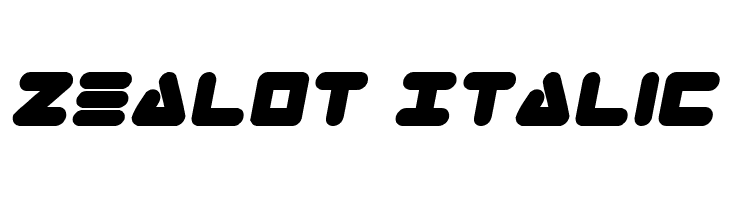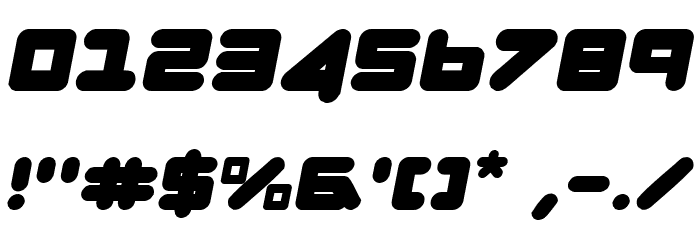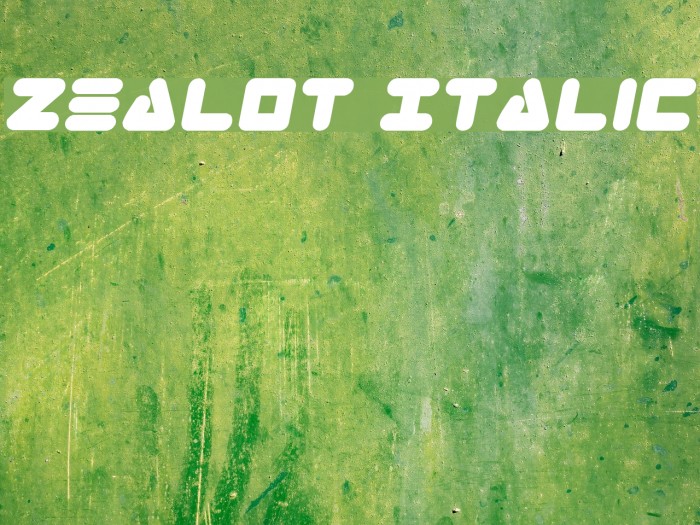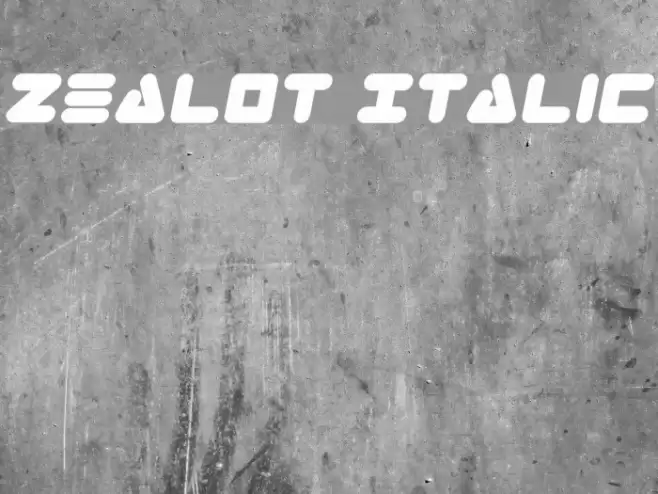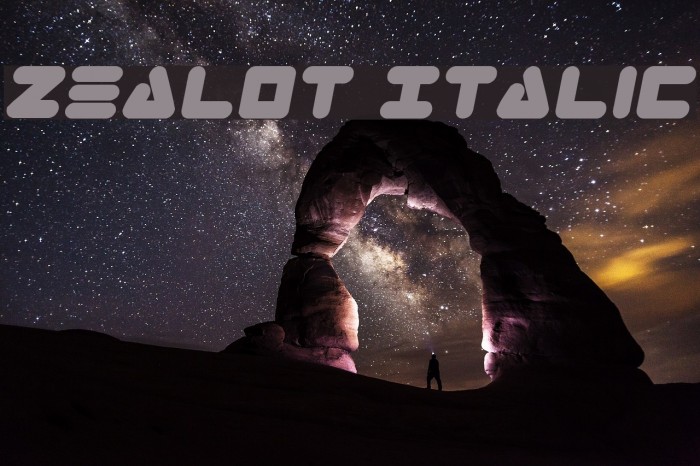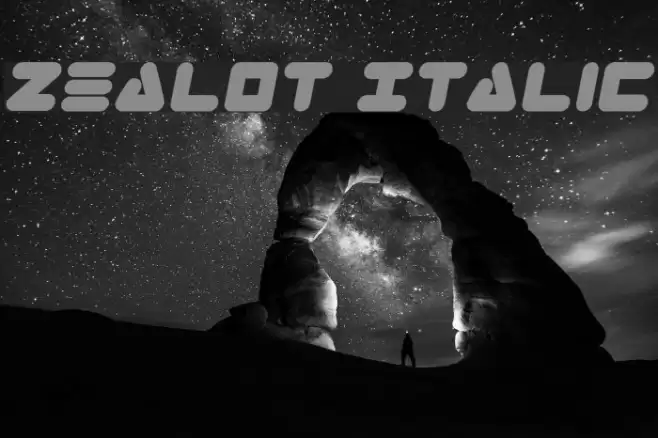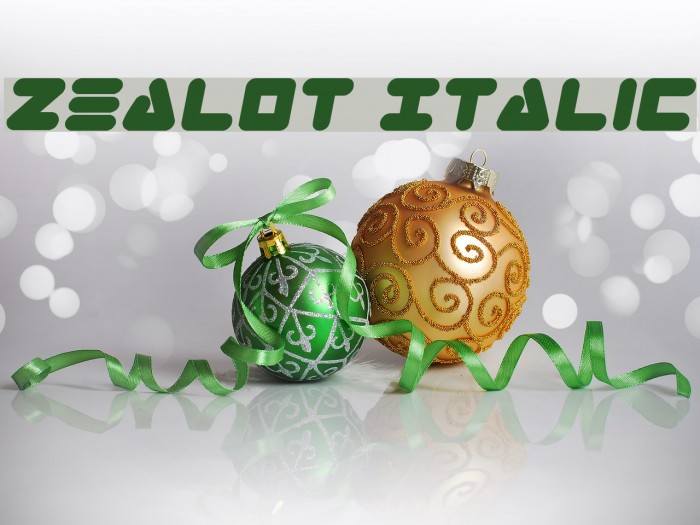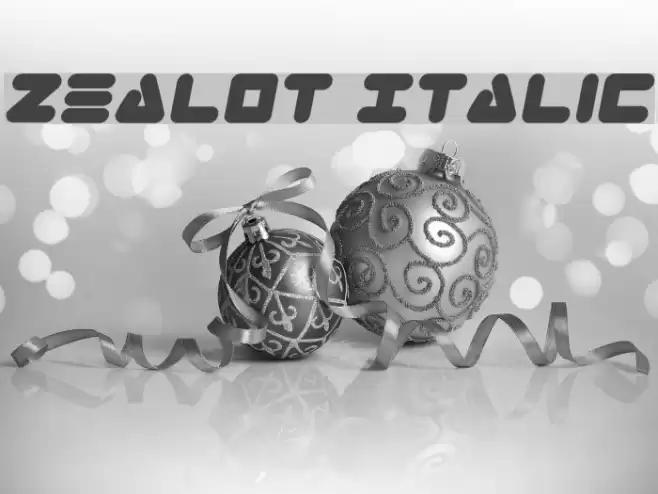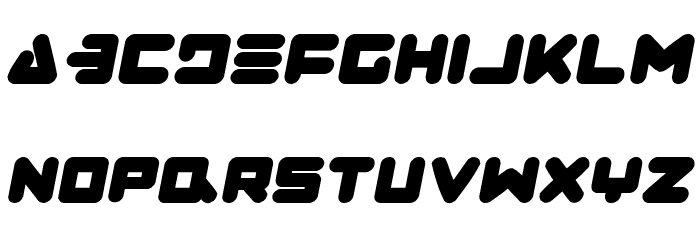
Zealot Italic Font
✎ Sci-fi
| Kategorien | Sci-fi |
| Anwendungsfall | Logos, Headlines |
| Vorgeschlagene Projekte | Ideal for technology branding, sports logos, modern advertising, and dynamic presentations. |